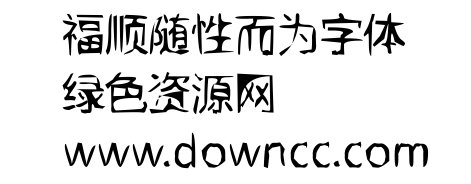
隨性而為字體
福順隨性而為體是一款筆畫(huà)隨意、造型端正的藝術(shù)字體,濃淺不一明暗相間,給你個(gè)性十足的觀賞好感,如果你也喜歡就來(lái)綠色資源網(wǎng)試試吧!
福順隨性而為字體特色
隨性而為,根據(jù)自己的本性來(lái)做事情,尊重自己內(nèi)心最真實(shí)的想法,是個(gè)褒義詞,主要強(qiáng)調(diào)不做作,真性情!
福順系列字體均是特色鮮明的藝術(shù)設(shè)計(jì)字體,不同于手寫(xiě)字體的恣意灑脫,不同于書(shū)法字體的大氣清揚(yáng),它有著自己的個(gè)性魅力,端正中有著一些游離,嚴(yán)肅中又有著一絲活潑,給你亦正亦邪、張弛有度的清新體驗(yàn)。
福順隨性而為體延續(xù)了福順字體的個(gè)性特色,給你非濃墨重彩的厚重感和明暗有度的飽和感,給文字更加超脫的視覺(jué)呈現(xiàn),可以廣泛運(yùn)用在海報(bào)設(shè)計(jì)、logo設(shè)計(jì)、印刷排版等方面!